今回は、Youtubeの「サムネイル」デザインで人気あるおすすめの日本語フリーフォントをまとめてみました。
Youtubeの「サムネイル」デザインは動画を視聴もらえるかどうかの入口になっているので、とても重要です。そんなサムネイルにどんなフォントを使うかによって、視聴率や視聴回数が大きく異なってきます。
今回は、Youtubeのサムネイルデザインでよく利用されていて、人気あるフリーフォントをご紹介します。サムネイルを目立たせることも大切ですが、動画のイメージにあっているかなどを大切です。サンプル画像を確認しながらフォント探しの参考にしてみてください!
以下のサンプルは、本記事で紹介しているフォントの一部ですが、フォントによってサムネイルから受ける印象が異なるので、表示する文字・発信する内容によってフォントを変えてみてくださいね。
以下から、フォントの紹介をしていきます!
キルゴUフォントは、ゴツゴツした太めのウェイトでインパクトがあり、元気のある様子が見えるデザインです。サムネイルやテロップでとても人気の高く定番フォントの1つです。
けいふぉんと!は、アニメ『けいおん!』のロゴタイプをヒントに作成したフォントです。一般的なゴシック体より手書きのような躍動感あるフォントなので、ほどよいポップな印象がゴシック体でしっかり見せつつ、少しポップな印象にできるフォントです。
源暎ぽっぷる
源暎ぽっぷるフォントは、手書き風な曲線が可愛いらしいPOP体風仮名のゴシック体フォントです。女子が書いたようなコロコロと丸っこい雰囲気なので、柔らかいトーンのサムネイルを作りたいときにぴったりです。
源暎エムゴ
源暎エムゴフォントは、、極太でどっしりしているベーシックなゴシック体フォントです。
どんな動画ジャンルのサムネイルでもあうフォントです。
雨墨ゴシック
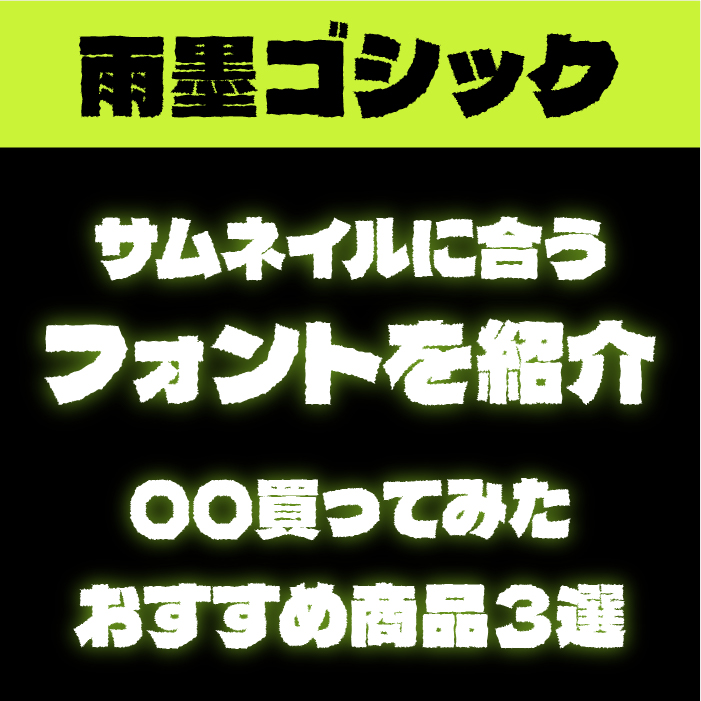
雨墨ゴシックフォントは、輪郭をギザギザなにじみの加工を施しているゴシック体フォントです。にじんだ雰囲気がカッコいいので、印象的なタイトルや見出しデザインになります。
チェックポイント★リベンジ
チェックポイント★リベンジフォントは、独特の極太の太さのバランスをもち、文字の線の太さのバランスなどできるだけ統一されたポップなフォントです。
トガリテ
トガリテフォントは、文字の先端にトゲトゲの装飾されているデザインフォントです。トゲがアクセントになっており、印象的なサムネイルデザインになること間違いないフォントです。
零ゴシック
零ゴシックフォントは、ガラスのように文字が割れていたり欠けていたり加工が施されているインパクトあるフォントです。インパクトがあるフォントなので、最近ではとっても人気があり、さまざまなYoutuberさんのサムネイルで利用されているフォントです。
デラゴシック
デラゴシックワン(Dela Gothic One)フォントは、超極太フォルムでどっしりとしているインパクトがある平体フォントです。デザインにインパクトを出すならこのフォントがおすすめです。
瀞ノグリッチ黒体
瀞ノグリッチ黒体フォントは、グリッチエフェクトの効いたフォントになっています。
SFやファンタジー系の動画内容にぴったりのフォントです。
異世明
異世明フォントは、異世界にワープする際のグニャッとしたイメージをフォントで再現しているフォントです。
こちらのグニャッとした加工が、ちょっと違和感があることで、視線を奪うサムネイルが作れるフォントです。
ニコカ
ニコカフォントは、硬すぎる印象ではなく、硬すぎず緩すぎずとちょうど良いバランスの文字になっています。
コーポレートロゴ
コーポレートロゴフォントは、Youtubeの黎明期から人気あり、定番のフォントです。
とりあえず、「迷ったらこれ使え!」と言われているフォントなので、どんなジャンルのサムネイルでも汎用的に使える素敵なフォントです。
源界明朝
源界明朝フォントは、限界ギリギリまでグランジ加工されているフリーフォントです。とてもインパクトがあるので、サムネイルはもちろん、テロップや字幕などにも向いているフォントです。
暗黒ゾン字
暗黒ゾン字フォントは、ホラー系フォントです。ミステリー系・ホラー系のYoutube動画などにぴったりなフォントです。文字を見ているだけでも恐怖感を煽られるので、つい見たくなってしまうサムネイルが出来上がりそうです。
玉ねぎ楷書激
玉ねぎ楷書激フォントは、毛筆で力強く書かれたインパクトある筆フォントです。
サムネイルに筆文字は合うかな?と思いますが、筆文字がよいアクセントになってサムネイルのデザインなどにハマるフォントです。
でらすこゴシック
でらすこゴシックフォントは、上記で紹介している「デラゴシック」を縦に伸ばして変形したフォントです。インパクトや印象はそのままで横幅が縮んだので、サムネイルにも使いやすくなっているフォントです。
源暎Nuゴシック
源暎Nuゴシックは、モダン極太なゴシック体となっているので、幅広いジャンルで活用できるフォントです。
源暎きわみゴ
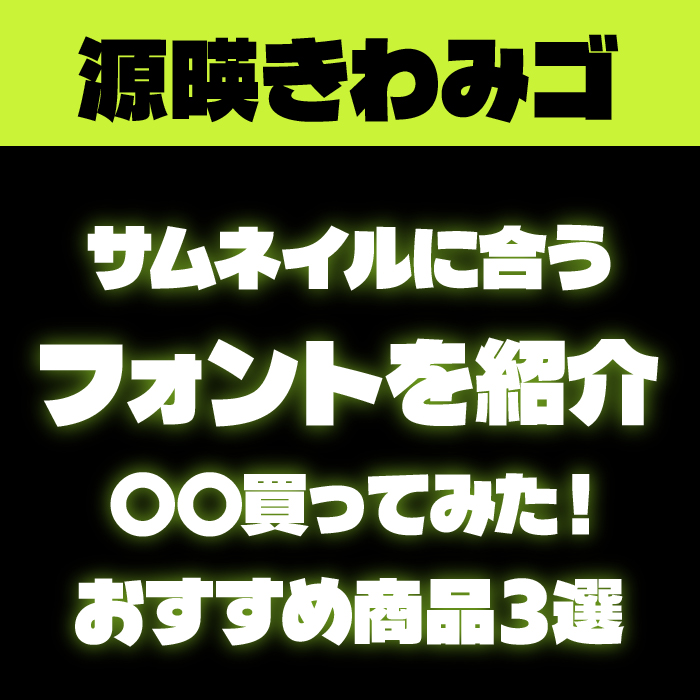
源暎きわみフォントは、超極太フォントで視認性・判読性も高く、強い印象があり、目を引くフォントなので、サムネイルにぴったりなフォントです。